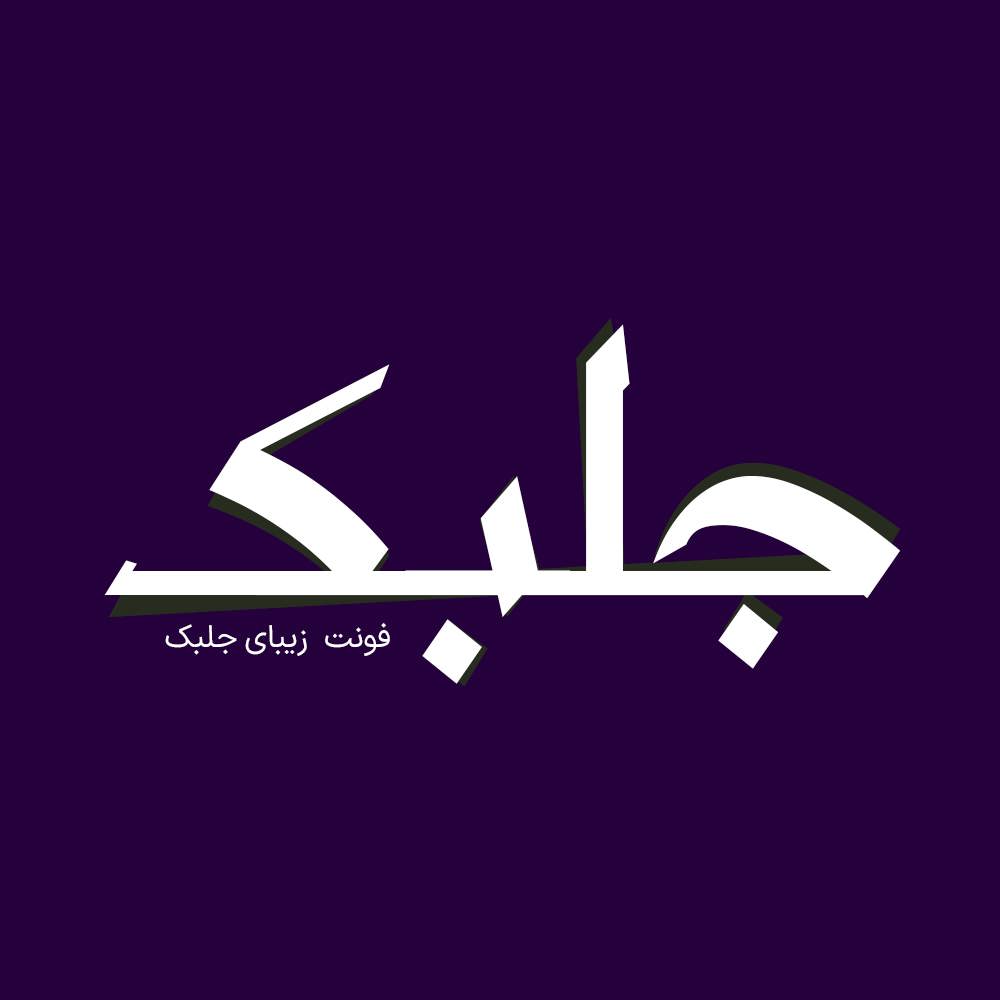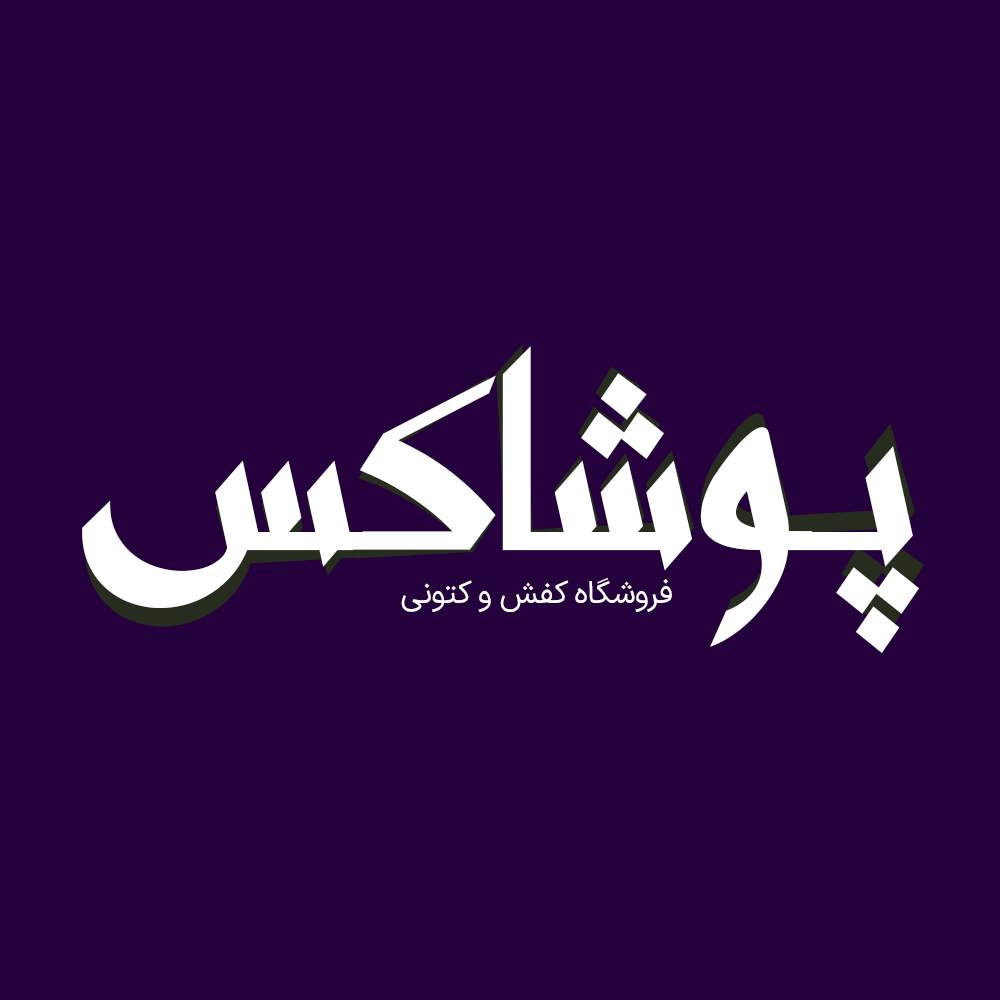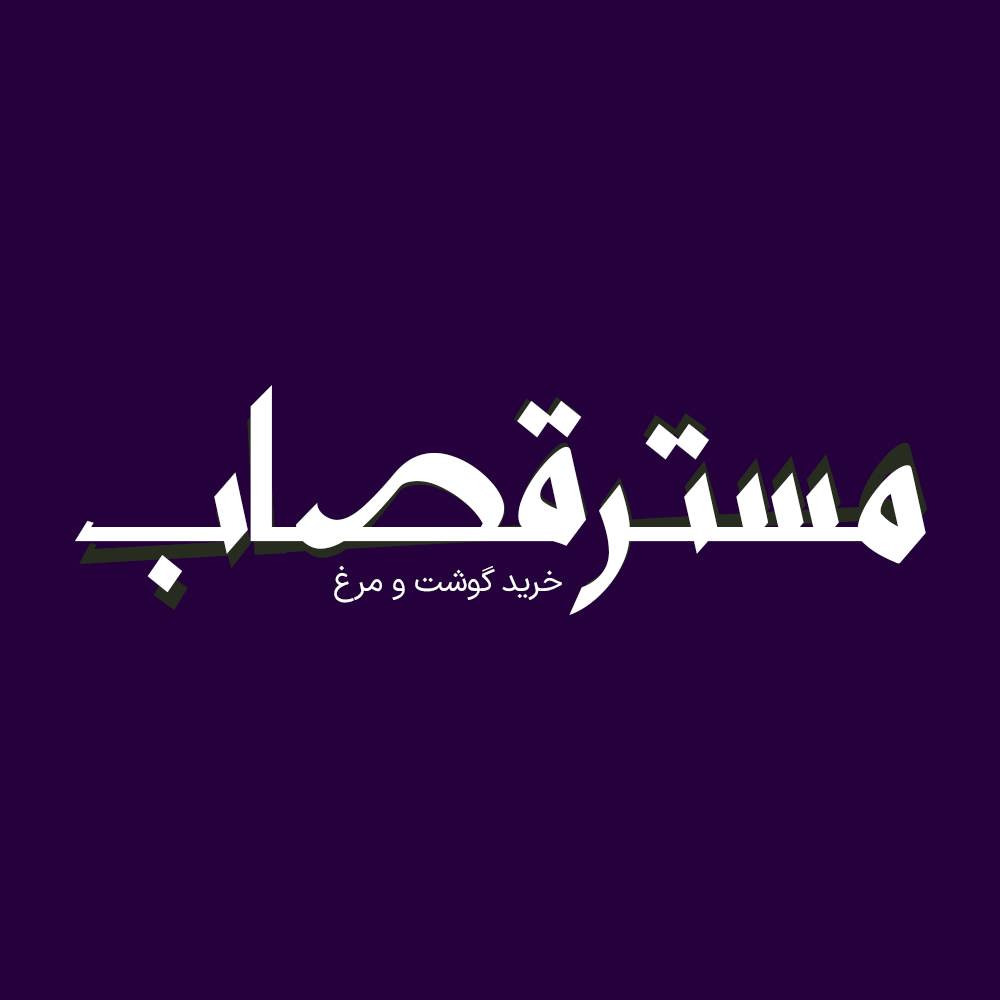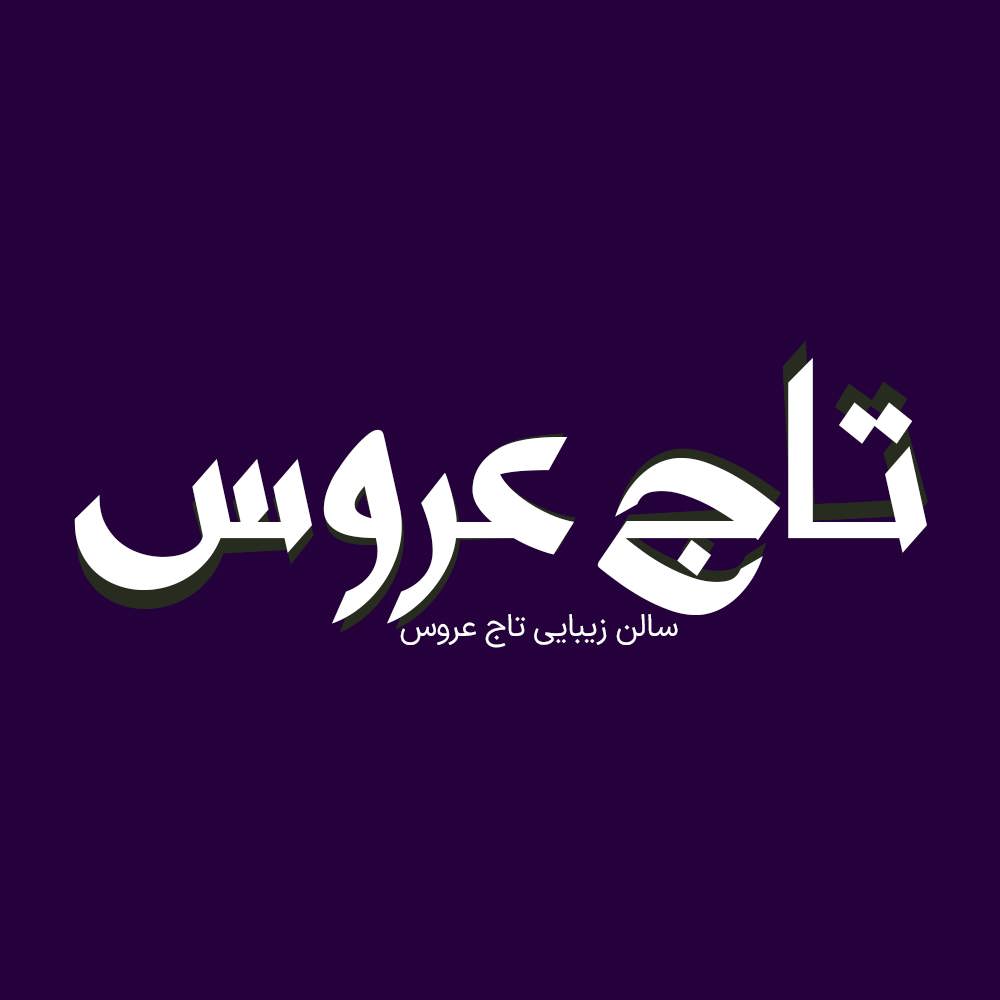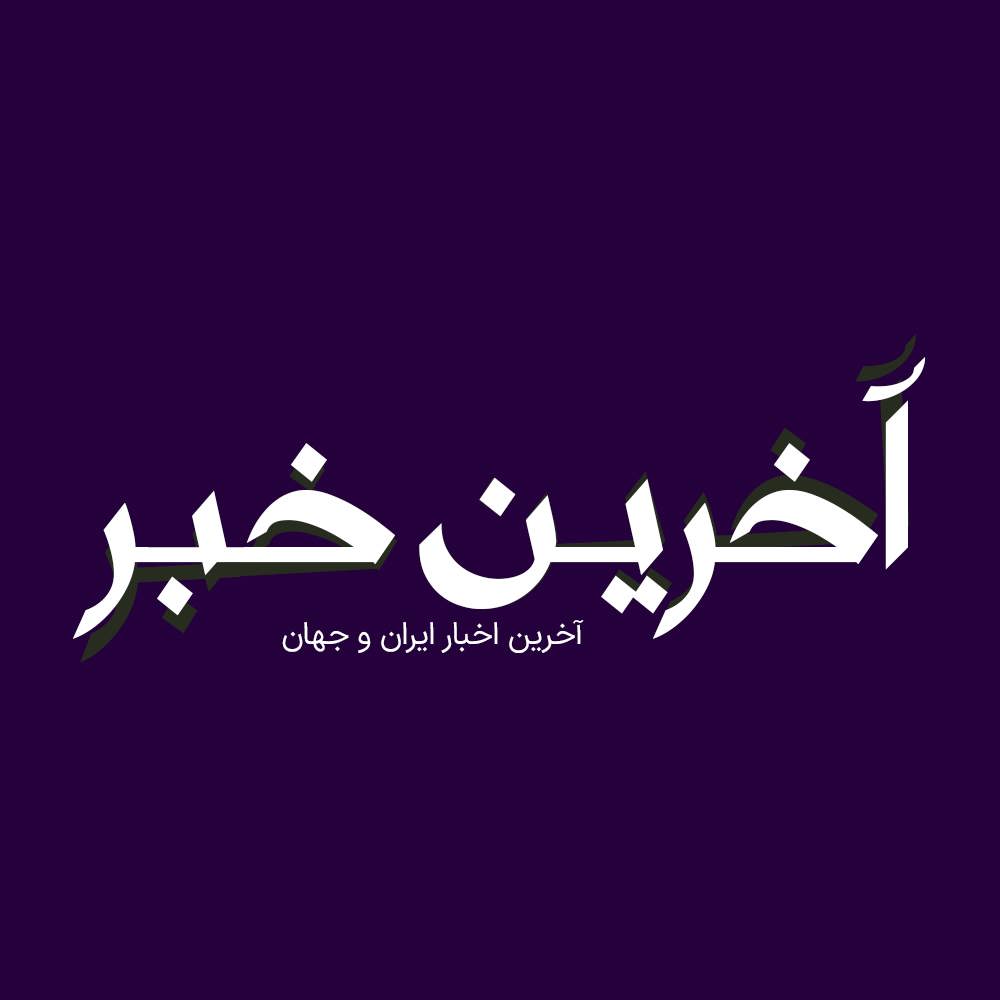
فونت فارسی جلبک Jolbak Font
فونت فارسی جلبک ظرافت و زیبایی را به دنیای دیجیتال می آورد و برای ایجاد یک تجربه بصری منحصر به فرد و مجلل با حفظ اصالت…
فونت فارسی جلبک ظرافت و زیبایی را به دنیای دیجیتال می آورد و برای ایجاد یک تجربه بصری منحصر به فرد و مجلل با حفظ اصالت و هویت ایرانی طراحی شده است. فونت جلبک یک فونت تک وزن با کاربرد طراحی لوگوتایپ و طراحی های مختلف همچون کتاب و تولید محتوای متن های کوتاه و عناوین می باشد و با ساختار حروف خود مناسب استفاده در لوگوهای نوشتاری می باشد. همچنین از فونت جلبک در طراحی تابلوهای چلنیوم هم به دلیل ساختار منحصر به فردش می توانید استفاده کنید. فونت فارسی جلبک زیبا و حرفه ای مناسب استفاده در عناوین و تیترها و جملات نسبتا کوتاه و هم طراحی انواع لوگوتایپ، تکست گرافی و استفاده در طراحی های خاص می باشد.
پیشنمایش و نمونه تایپ های فونت جلبک